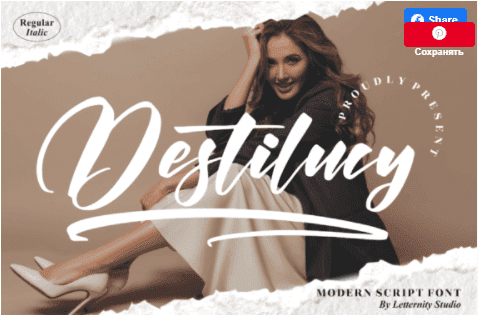
Название: Destilucy Font (2022)
Destilucy — красивый рукописный шрифт, подходящий для любых проектов, таких как логотипы, брендинговые проекты, дизайн товаров для дома, упаковка продуктов, кружки, цитаты, плакаты, сумки для покупок, футболки, обложки книг, визитки, пригласительные билеты, поздравительные открытки, этикетки. , фотографии, водяные знаки, специальные мероприятия и все другие ваши прекрасные проекты, которые требуют красивого вкуса сценария.